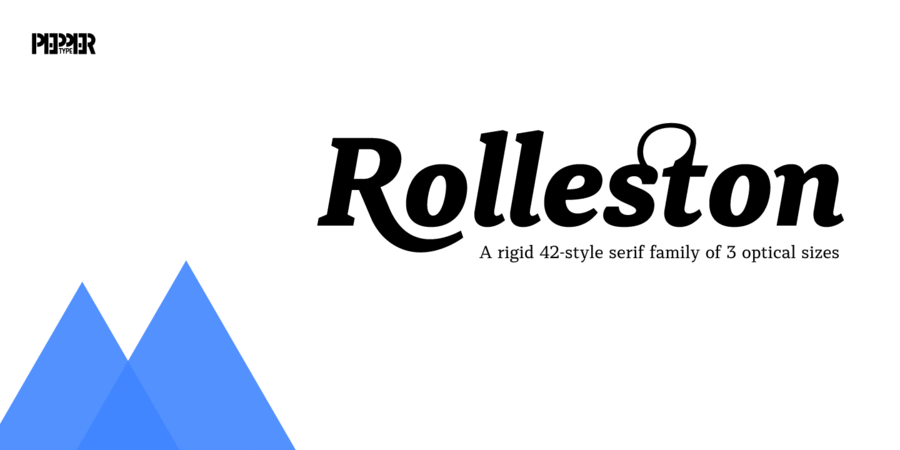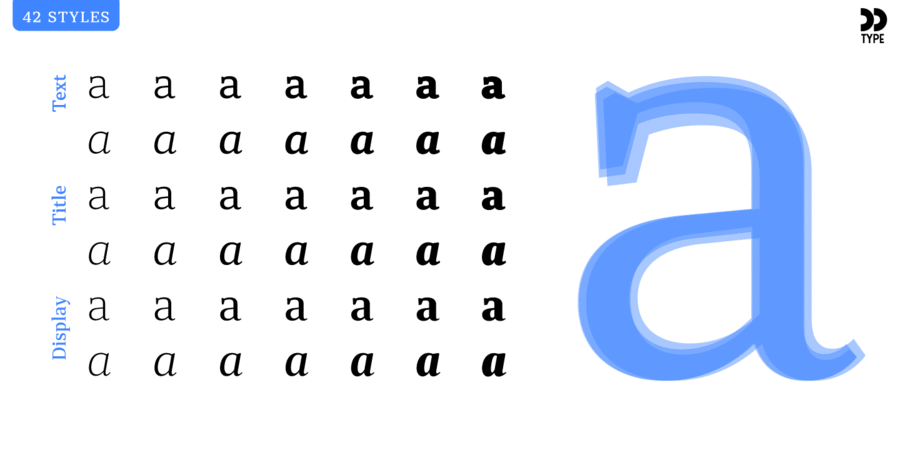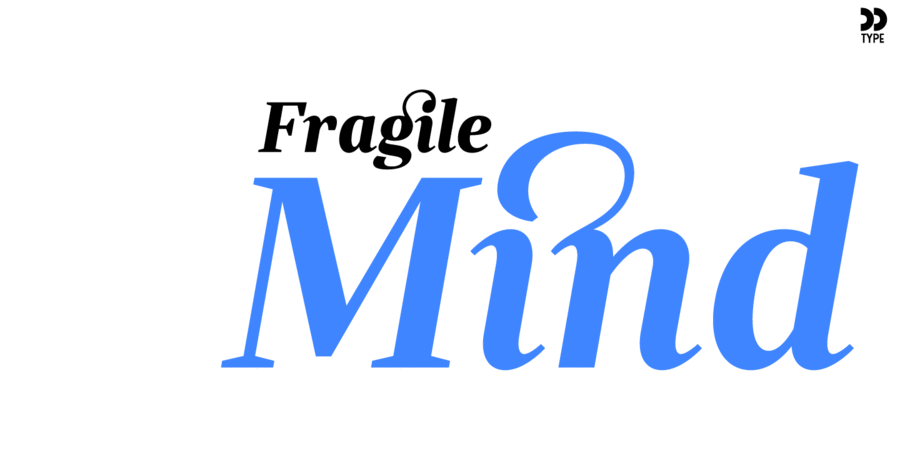
Rolleston Display – частина шрифтового сімейства Rolleston. Його 14 накреслень спеціально адаптовані для акціденції, наприклад великих написів на плакатах і обкладинках.
Rolleston – статичне шрифтове сімейство з клиноподібними зарубками. Гарнітура містить 42 накреслення, по 14 для трьох оптичних розмірів: Text, Title, та Display.
Ця гарнітура підтримує десятки мов на латиниці та кирилиці, містить різні опентайп-фічи, безліч лігатур і великий набір альтернативних гліфів. Це дозволяє створювати унікальні заголовки та красиві збалансовані тексти.
Шрифт розробив Олег Ліщук у 2018 році.
Асоціації з сімейством шрифтів Rolleston DisplayОсобистість і характер гарнітури:
тонкий, легкий, делікатний, рівний, гармонійний, технічний, сучасний, точний, логічний, статичний, культурний, освічений, серйозний, розумний, твердий, чіткий, різкий, гострий, розкішний, гламурний, модний, ювелірний, художній, худий, ввічливий, динамічний, витончений, елегантний, стійкий, ефектний, якісний, елітний, дорогий, багатий, міський, добірний, благородний, красивий, майстерний, естетичний, виразний, пластичний, приємний, акуратний, гнучкий, формальний, стабільний, солідний, романтичний, переконливий, класичний, інтелігентний, аристократичний, салонний, урочистий, дзвінкий, вишуканий, музичний, прекрасний, блискучий, знаменитий, дорогоцінний, комільфо, оригінальний, глянцевий, гордий, срібний, сріблястий, театральний, драматичний, творчий, сексуальний, яскравий, тактичний, мотивуючий, відповідальний, авторитетний, значний, важкий, щільний, помітний, активний
Місто, література, дизайн, косметика, краса, гламур, Інстаграм, преміум, шоколад, парфуми, готель, прикраса, романтика, кохання, годинник, костюм, взуття, одяг, розкіш, мода, театр, опера, музей, музика, вино, ресторан, срібло, перукарня, парфумерія, ювелір, драма, комільфо, бутік, вечір, люкс, Трофей, нагорода, захід сонця Гарнітура має ознаки стилів: